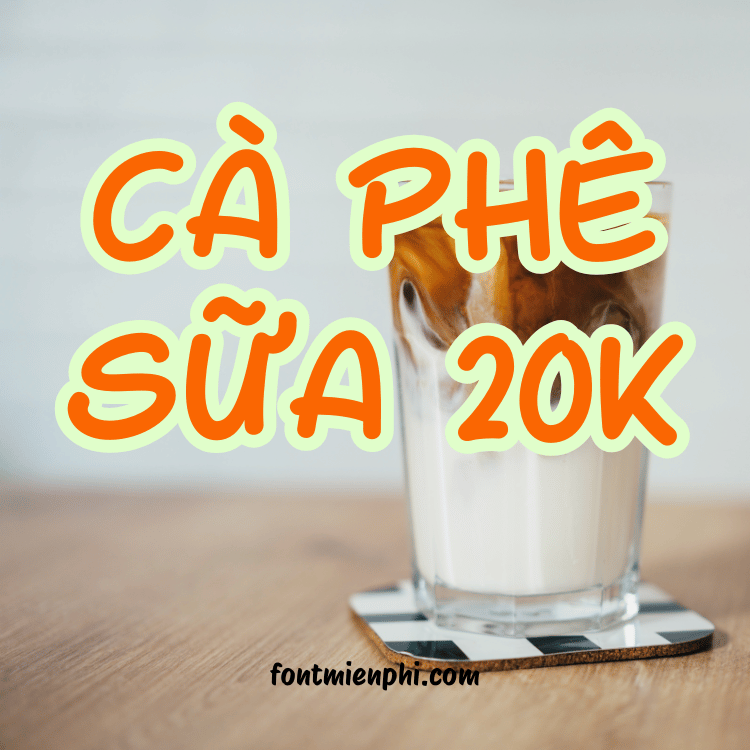
Font Việt hóa FMP Mulled Wine Season – Nét Chữ Sang Chảnh, Độc Đáo
Font Việt hóa FMP Mulled Wine Season là một trong những font chữ đẹp, độc đáo với phong cách sang trọng, phù hợp cho thiết kế poster, bìa sách, logo, và các dự án sáng tạo. Font được tối ưu cho tiếng Việt, đảm bảo hiển thị sắc nét, mượt mà trên mọi nền tảng.
Đặc điểm nổi bật của Font Việt hóa FMP Wine Season
Thiết kế tinh tế: Nét chữ thanh lịch, phóng khoáng, phù hợp với thiết kế cao cấp.
Hỗ trợ tiếng Việt: Đầy đủ dấu, không lỗi font, tương thích với mọi phần mềm thiết kế.
Đa dạng ứng dụng: Dùng cho in ấn, quảng cáo, social media, branding…